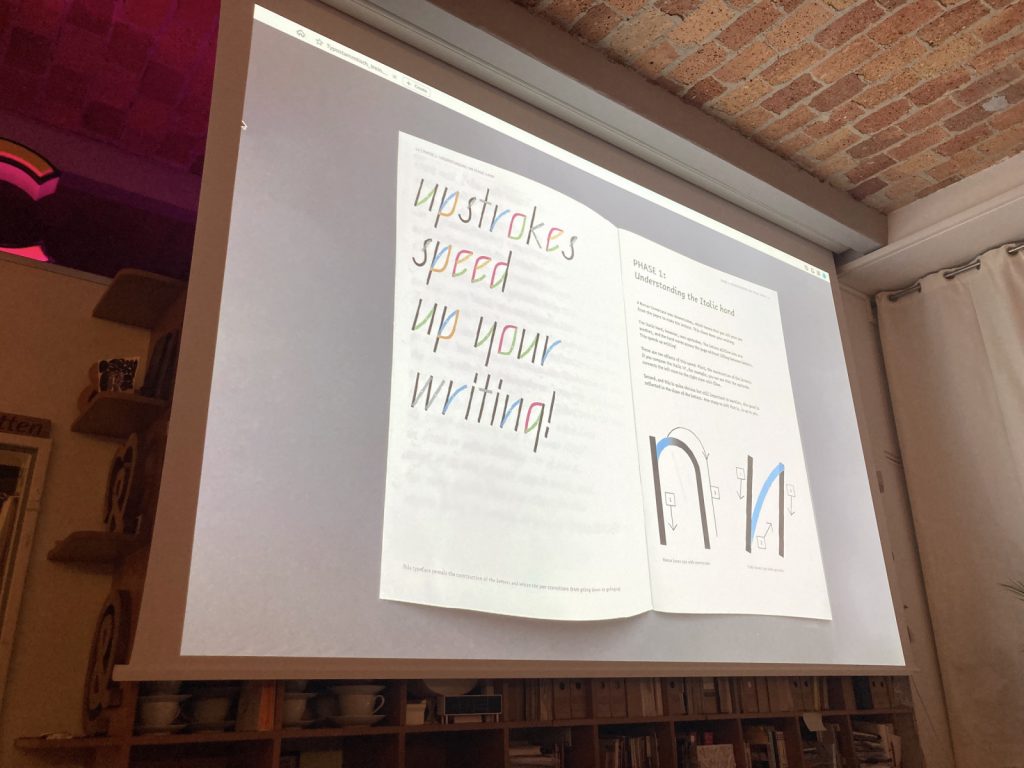
Im Spätsommer steht wieder ein Schriftspaziergang an. Flo und Fritz zeigen uns dieses Jahr den Klassiker: die interessantesten Schriftfundstücke in Mitte. Anschließend treffen wir uns im Prater-Biergarten – auch das ein Klassiker – und freuen uns, wenn ihr zahlreich dazustoßt.
Der sommerliche Stammtisch-Stammtisch findet im Prater Biergarten statt. Kommt vorbei, um zu quatschen, Entwürfe und Fundstücke zu zeigen und euch mit anderen Schriftbegeisterten auszutauschen. Für Regenwetter gibt es eine großzügige Überdachung.
Die Titelzeile ist im kursiven Schnitt der Wurstvogel Grotesk von Stefan Zwickl gesetzt. Die Schrift soll dieses Jahr noch erscheinen.Das Titelbild zeigt Schriftspaziergang und Stammtisch-Stammtisch aus den Jahren 2024 und 2021.
An einem der bisher heißesten Abende des Jahres, am 25. Juni, haben wir das Studio LucasFonts gut heruntergekühlt und entsprechend viele Getränke bereitgestellt. Zum 129. Typostammtisch und zum dritten Verlagsabend, einem relativ neuen Veranstaltungsformat (seit 2023) in unserer 20-jährigen Geschichte, haben wir erneut Gäste eingeladen, die unsere Erwartungen an typografische Gestaltungskonzepte dann aber noch mal übertreffen.
Luc(as) de Groot und Sonja Knecht begrüßen die Gäste; der Saal ist voll. Los geht’s.
ztscrpt – Alexander Wolff undYves Mettler Ein Magazin ist eine Schrift ist ein Magazin ist … „Wir sehen jedes Heft wie eine Ausstellung“
Chicago, Times, Plotter, TheMix, Princess Lulu, Karloff, LiebeRuth, New Paris oder Serifbabe, so heißen die Ausgaben der 2002 in Wien gegründeten Kunstzeitschrift mit dem unaussprechlichen Pseudonym ztscrpt (welches aber nicht sichtbar vorkommt); das typografische Magazin ohne fixen Namen also, das jeweils die verwendete Schrift als Titel verwendet, und deshalb immer anders heißt, und dementsprechend schwer zu finden ist. Hierbei handelt es sich um ein typografisches Gesamtkonzept. Bereits 2005 wurde es vom London Design Museum in der Ausstellung Best European Design gewürdigt.
Von den bisherigen sieben Herausgeber·innen sind Yves Mettler und Alexander Wolff bei uns.
Sie stellen die aktuellen Ausgaben vor: Nr. 42 Ghost von Juli 2025 und Ana Diego, die ganz frische Ausgabe 43, Juni 2026. Die jeweilige Schriftart und mehr noch der Name der jeweiligen Schrift fungiert als inhaltlich-atmosphärische Leitlinie nur begrenzt, mehr in ihrer Visualität. Das habe mit ihren Bezügen nach Wien zu tun, so Yves. Passenderweise ist Gerhard Rühm, letzter lebender Vertreter der Wiener Gruppe, in Ausgabe 42 Ghost mit Gedichten vertreten. Aber wie wählen sie die Schriften aus? „Einerseits random“, sagt Yves, „am Anfang, da haben wir Klassiker wie Chicago, Helvetica und DIN gemacht“, und es gehe unter anderem auch darum, „wie die Beiträge mit den Fonts zusammenspielen. (…) Wir sehen jedes Heft wie eine Ausstellung auf Papier.“
Das Heft habe immer das gleiche Format, erklärt Alexander, Fotografie auf dem Cover, Inhaltsverzeichnis vorn, Impressum hinten drauf, und ja, es sei schon zum Lesen gedacht (angesichts der superbreiten Textblöcke und Nachfragen aus dem Publikum), „aber wir wollten maximal auf Design verzichten“. In der Zusammenarbeit mit Tauba Auerbach und mit ihrem Font FIG sei das Ganze so wahnsinnig schön, aber so wahnsinnig schwer zu lesen geworden, „dass wir dann alle Texte als Poster in Arial dazugelegt haben“. Das Magazin sei mit ihnen gealtert, erklärt Alexander anhand der inneren Randspalte, die nun immerhin zwei Zentimeter Luft zum Rand lässt und damit die breit laufenden Zeilen einen Hauch besser erfassbar macht als in den Anfängen, aber wirklich nur einen Hauch. In den Anfängen klebte der Satzspiegel fast direkt an der Außenkante und im inneren Bund des Blattes.
Die Publikationen beinhalten jeweils 10 bis 15 Beiträge ausgewählter Künstler· und Autor·innen, entsprechend den künstlerischen Interessen der Herausgeberschaft. Sie erscheint seit Beginn in einer festen Auflage von 300 Exemplaren, wird vom österreichischen Bundeskanzleramt mitfinanziert und ist in Kunstbuchhandlungen in Berlin, Wien und in Brüssel erhältlich oder per Mail zu bestellen (anfangs für 3 Euro, jetzt, nach 24 Jahren, für 5 Euro pro Heft); das Online-Archiv bietet die Cover und Inhalte aller Ausgaben im Überblick: ztscrpt.
Noch bis zum 14. Februar zeigt die Galerie Vincenz Sala schriftbasierte Kunst in ihrer PAROLES group show II. Um Scherenschnitte geht es in der Ausstellung „Schere–Stil–Papier. Lettegrafik x Johanna Beckmann“, zu sehen bis zum 1. März im Kulturforum. In der Berlinischen Galerie läuft bis zum 16. März die Ausstellung „Raoul Hausmann: Vision. Provocation. Dada“ mit collagierter Schrift. Die Fontstand-Konferenz kommt nach Berlin! 10.–11. April, Silent Green, Tickets und Workshopplätze sind bereits buchbar. Bis zum 12. April kann man die Ausstellung „ENTWERTER/ODER und das sogenannte Zeitschriftenunwesen“ im Willy-Brandt-Haus besuchen. Dort wird es einen Filmabend am 26. Februar geben. Im Humboldtforum sind Manuskripte verschiedener Sprachfamilien in einer Wechselpräsentation mit dem Titel „Sprachfamilien“ zu sehen – noch bis Mitte des Jahres.
Die Titelzeile ist gesetzt aus Britts Schreibanleitungsschrift.